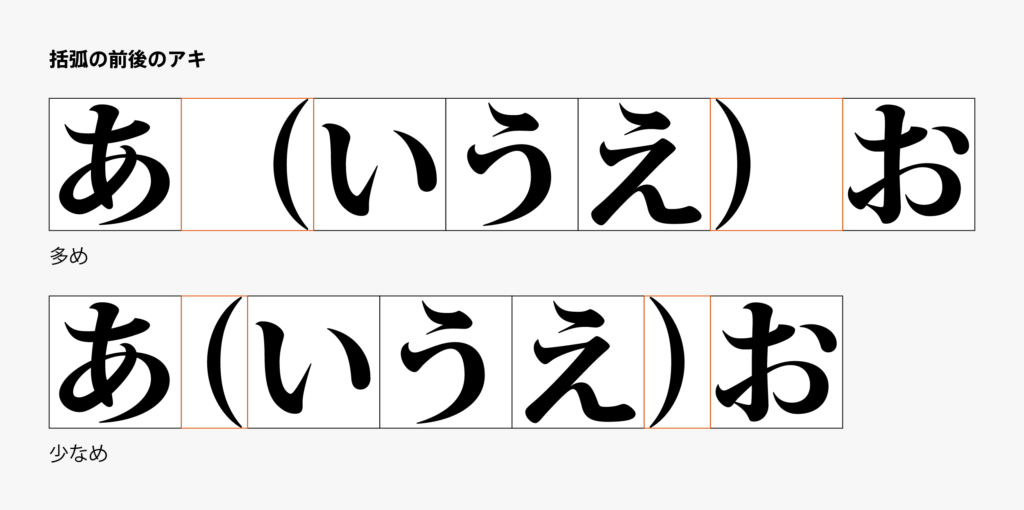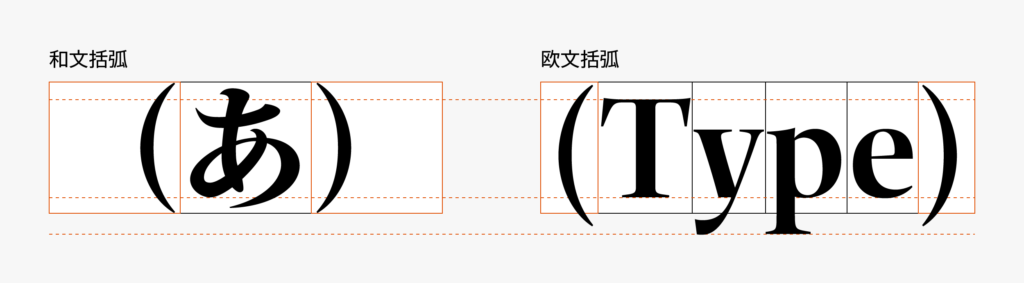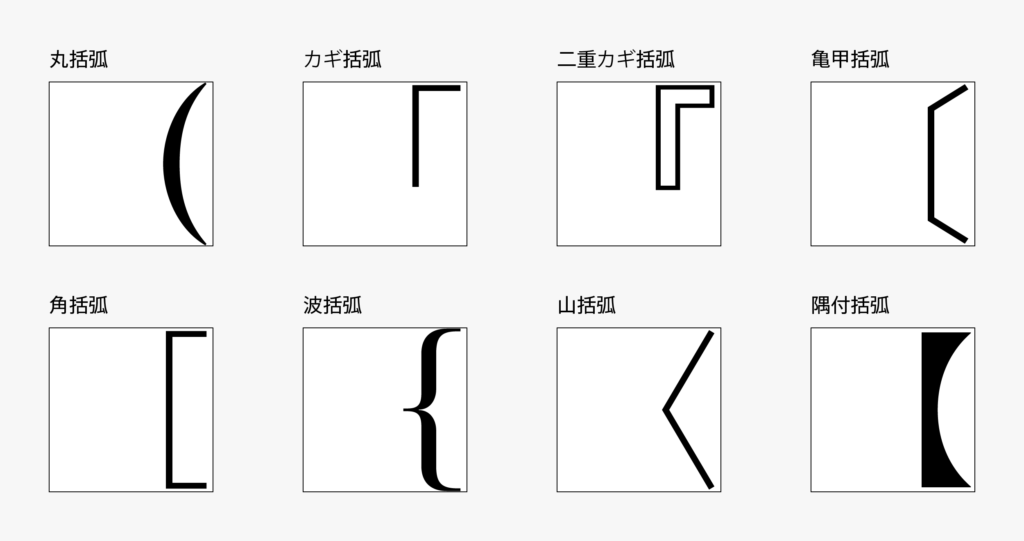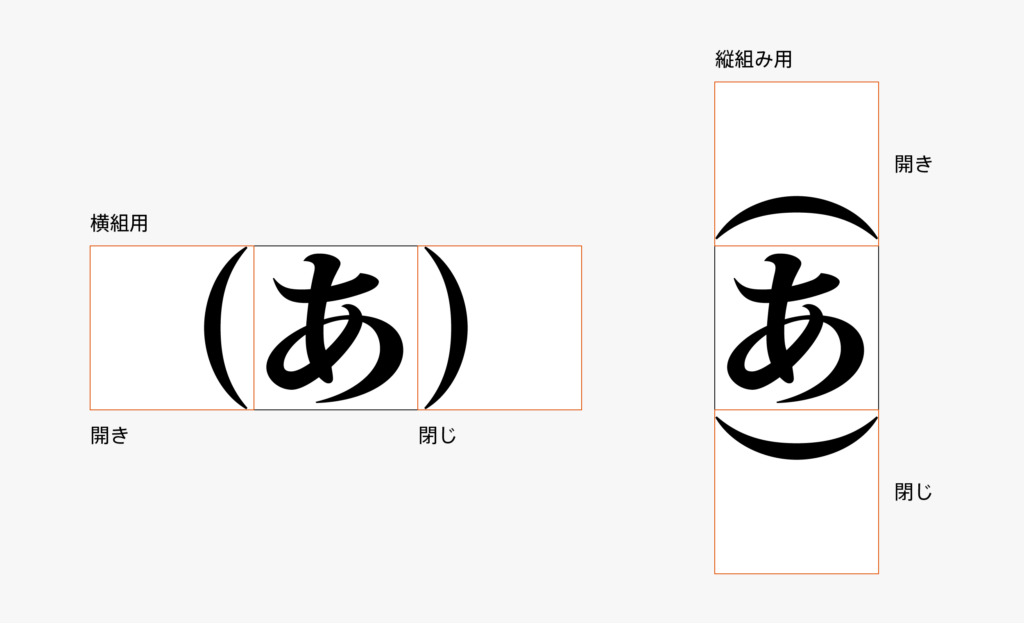
和文約物03「括弧」
今回はどうにもややこしい括弧類のお話です。丸括弧()やカギ括弧「」のようにいくつかの種類がある上に、それぞれに開きと閉じ、横組み用と縦組み用、全角と半角、と必要なグリフを考えるだけでもちょっとややこしく思えてきます。
括弧のデザインで気をつけたいのが、全角の括弧でも半分の幅でデザインするという点です。組版の括弧前後のアキには様々な設定があるため、半分の幅を超えてデザインすると隣の文字とくっついてしまうことがあります。全角括弧とは別に半角括弧もあるのですが、組版で使われるグリフは基本的に全角の方です。
一部の括弧では和文用と欧文用をそれぞれ用意することがあります。正方形の枠の中で一文字一文字を作る和文と、ベースラインの上下に高さを設定する欧文、括弧もそれぞれの文字群に合わせて調整が必要です。和文に対して欧文括弧は少し下がって見えると時折言われますが、それはディセンダーをもつ欧文に合わせているからです。
一般的に半角括弧というと上記の欧文括弧を指すかと思います。しかし制作上の字幅区分において、欧文括弧は半角ではなくプロポーショナルであるのがやっぱりややこしいところです。